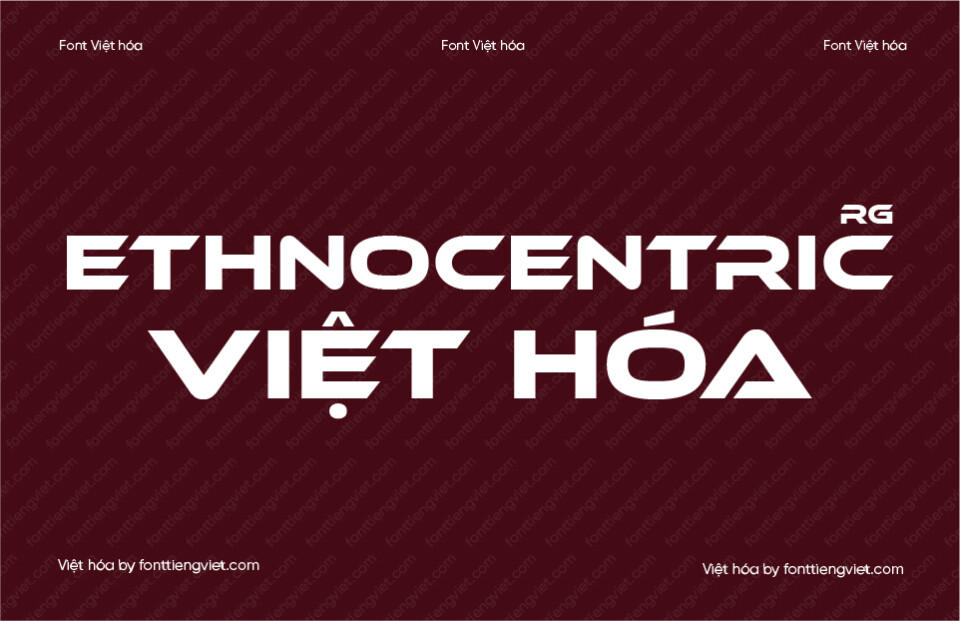
Font Việt hóa 1FTV VIP Ethnocentric Rg
Giới thiệu về Font Việt hóa 1FTV VIP Ethnocentric Rg trong thiết kế
Trong thế giới đồ họa hiện đại, việc lựa chọn một bộ Font Miễn Phí phù hợp đóng vai trò quyết định đến sự thành công của một tác phẩm. Một trong những cái tên đang thu hút sự chú ý của cộng đồng designer chính là Font Việt hóa 1FTV VIP Ethnocentric Rg. Đây là một bộ phông chữ mang phong cách tương lai, mạnh mẽ và đầy tính đột phá. Với các đường nét góc cạnh, dứt khoát nhưng vẫn đảm bảo sự cân đối, bộ phông này cực kỳ phù hợp cho các dự án liên quan đến công nghệ, game, thể thao điện tử hoặc các tiêu đề phim khoa học viễn tưởng. Đặc biệt, phiên bản 1FTV VIP này đã được tinh chỉnh kỹ lưỡng về dấu tiếng Việt, giúp các nhà sáng tạo tại Việt Nam có thể sử dụng một cách mượt mà nhất mà không lo bị lỗi hiển thị.
Đặc điểm nổi bật của Font Việt hóa 1FTV VIP Ethnocentric Rg
Phong cách Futuristic độc đáo
Font Việt hóa 1FTV VIP Ethnocentric Rg nổi tiếng với cấu trúc chữ không chân (sans-serif) theo phong cách hình học. Mỗi ký tự đều toát lên vẻ hiện đại, tối giản nhưng vô cùng ấn tượng. Kiểu dáng của nó gợi liên tưởng đến những bảng mạch điện tử hoặc các công trình kiến trúc tương lai, giúp người xem cảm nhận được sự tiến bộ và không gian công nghệ cao. Khi sử dụng bộ phông này, các em học sinh hay sinh viên chuyên ngành mỹ thuật có thể dễ dàng tạo ra những slide thuyết trình sinh động hoặc các bìa báo cáo mang đậm dấu ấn cá nhân và chuyên nghiệp.
Khả năng hiển thị và tính ứng dụng cao
Mặc dù có thiết kế cách điệu, nhưng Font Việt hóa 1FTV VIP Ethnocentric Rg vẫn giữ được độ đọc tốt ở các kích thước lớn. Phông chữ này phát huy tối đa sức mạnh khi được dùng làm tiêu đề (heading), logo, hoặc poster quảng cáo. Nhờ vào việc tối ưu hóa bảng mã Unicode và các dấu thanh đặc trưng của tiếng Việt, người dùng có thể yên tâm sử dụng trong các phần mềm thiết kế phổ biến như Adobe Photoshop, Illustrator hay thậm chí là các ứng dụng văn phòng cơ bản. Sự đồng bộ giữa các ký tự giúp văn bản trông hài hòa, tránh tình trạng dấu bị lệch hoặc quá nhỏ so với mặt chữ chính.
Kết luận về bộ Font Việt hóa 1FTV VIP Ethnocentric Rg
Tổng kết lại, Font Việt hóa 1FTV VIP Ethnocentric Rg là một công cụ không thể thiếu trong kho tài nguyên của bất kỳ ai yêu thích sự sáng tạo. Với sự hỗ trợ tận tình từ các cộng đồng chia sẻ Font Miễn Phí, Font Việt Hóa, Font Việt hóa 1FTV VIP Ethnocentric Rg, việc tiếp cận những bộ phông chất lượng cao đã trở nên dễ dàng hơn bao giờ hết. Hy vọng rằng với gợi ý này, các bạn sẽ có thêm nhiều cảm hứng để tạo nên những sản phẩm đồ họa tuyệt vời, góp phần làm phong phú thêm thị trường thiết kế tại Việt Nam. Đừng ngần ngại thử nghiệm bộ phông này cho các dự án sắp tới để cảm nhận sự khác biệt mà nó mang lại. Bạn có muốn tôi hỗ trợ thêm về cách phối màu hay tìm kiếm hình ảnh minh họa phù hợp cho bộ font này không?